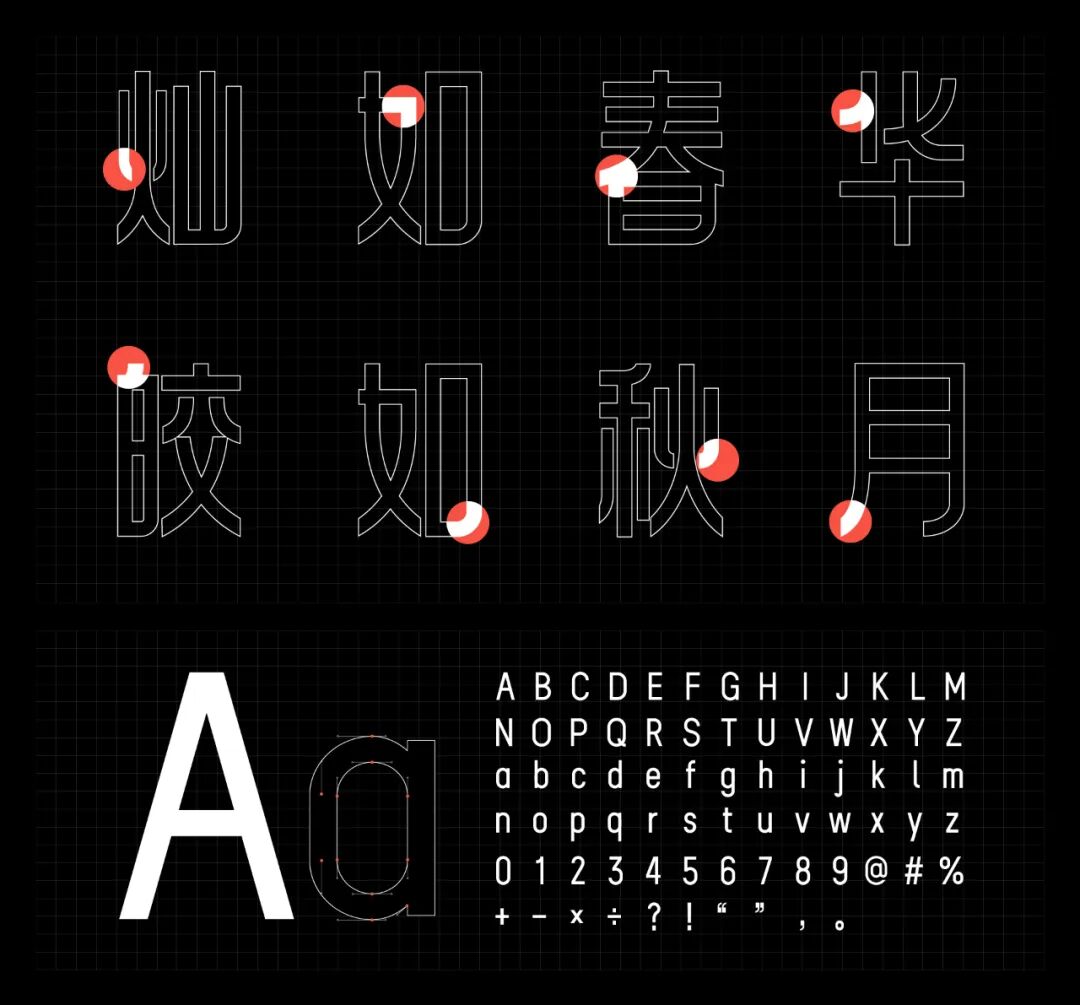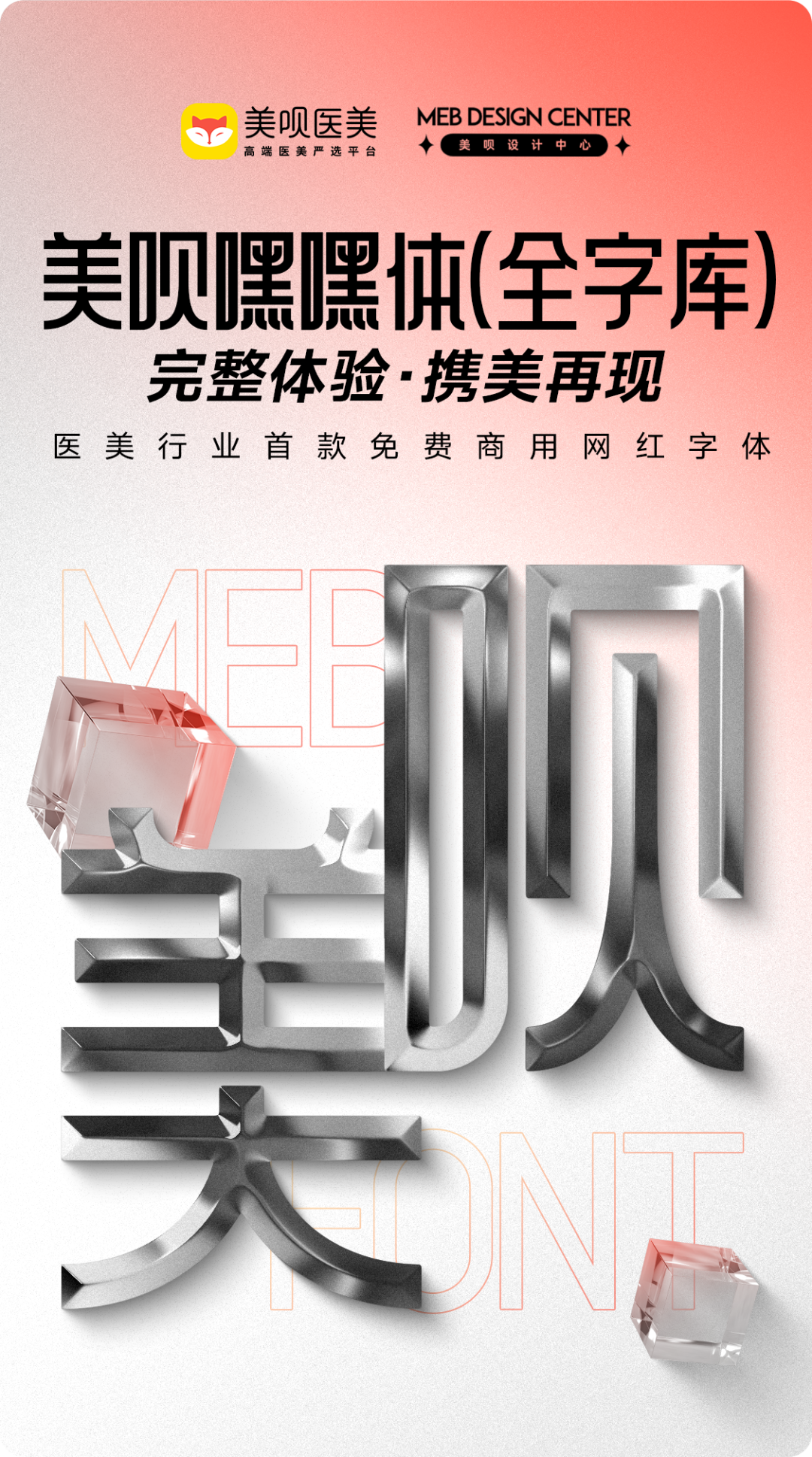
美呗嘿嘿体
字体简介
2021年11月1日,由美呗设计中心出品的首款免费商用字体【美呗嘿嘿体】试用版上线,包含2500+个汉字。
2022年末正式推出【美呗嘿嘿体】完整版啦!
美呗嘿嘿体,是由美呗设计中心主导设计的一款品牌字体,也是医美行业首款字体。之所以取名美呗嘿嘿体,一是因为这款字体本身属于黑体,二是融入了美呗人“乐观、皮实”的精神,故取名“美呗嘿嘿体”。
秉承公司文化价值观,设计团队在工作之余从构思到完成,整整花了两年半的时间,精心打磨出了一套符合现代美业的商用字体。
字体展示